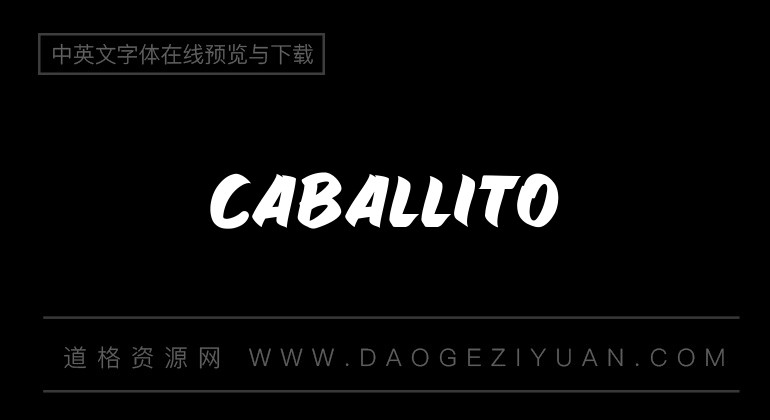
Caballito 是一款由设计师 Héctor Gatti 创造的免费字体,它的名字来自于西班牙语中“小马”的意思。这种字体特别适用于宣传册、海报和标题等大字体排版,因为它具有粗重的特点和明显的对比度,使得文字更加易于阅读和突显。 Caballito 字体具有不同的字重和斜体版本,适用于不同的排版需求。它的设计灵感来自于传统的印刷字体,但结合了现代的设计元素,使得它具有了独特的个性和特色。Caballito 字体还支持多种语言,包括西班牙语、英语、法语和德语等常用语言。 总之,Caballito 字体是一种适用于大字体排版的现代印刷字体,具有独特的设计风格和广泛的语言支持,非常适合用于宣传设计和品牌标识等方面。内容介绍
Caballito是一款非常不错的手写艺术字体,具有很好的视觉感,适合于文化类的宣传设计、商业类品牌的广告和产品包装设计以及个性化文字排版等较多场景。